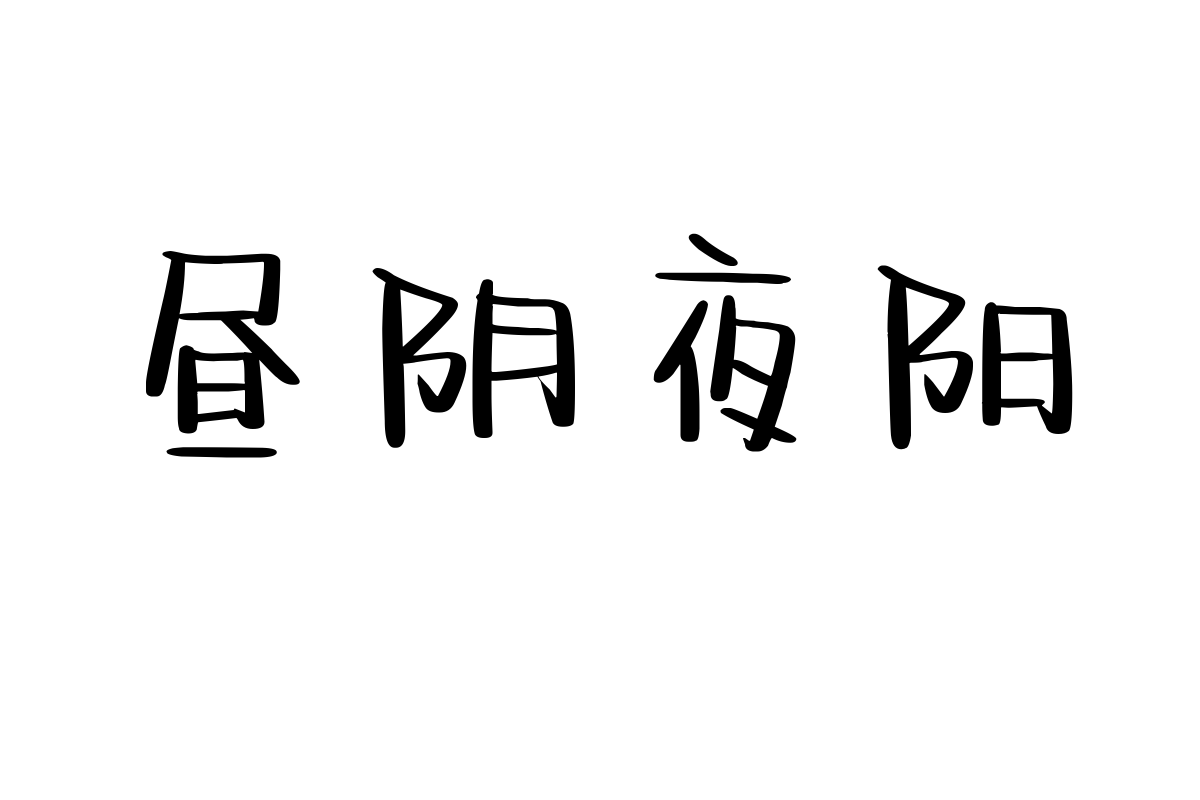
也字工厂春日公园体是一款现代中文字体,由也字工厂设计。该字体具有独特的设计风格,字形结构简洁明了,线条流畅自然。在春日公园体中,也字的笔画粗细适中,整体给人一种轻松、舒适的感觉。同时,春日公园体还注重细节处理,使得整体视觉效果更加和谐。这款字体适用于各种需要展示文字信息的场合,如广告、报纸、杂志等。